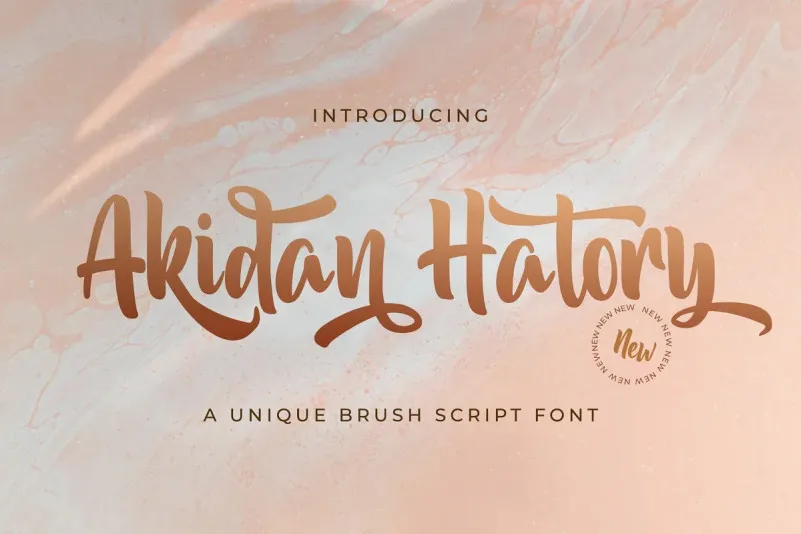
Akidan Hatory Script Font – Download Grátis
A Akidan Hatory Script Font é uma elegante tipografia script curvada e redonda criada pela StringLabs para designers que buscam um estilo vintage e único. Seu design é perfeito para criar marcas inovadores, dando vida a ideias mais criativas. Com sua abrangente gama de caracteres, esta fonte se destaca não apenas como uma ferramenta útil no seu arsenal gráfico, mas também como um elemento distintivo que pode transformar os seus projetos em algo realmente especial. Ideal para aqueles que buscam uma paleta de opções para dar vida a suas criações digitais, seja ela um site, um livro digital ou até mesmo uma camisa personalizada. Descubra por si mesmo o poder da Akidan Hatory Script Font e veja como sua visão criativa ganha vida com cada letra escrita.